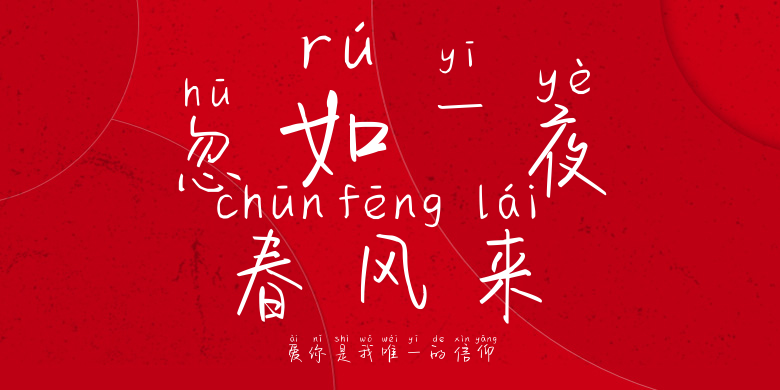
爱你是我唯一的信仰
爱你是我唯一的信仰,这款字体结构工整、笔画清晰,兼顾美观与易读性,适用于标题、正文、海报、包装、LOGO 等多种场景。字形优雅稳定,风格百搭耐看,适配日常排版与创意设计,让文字呈现更舒适、更具质感。爱你是我唯一的信仰一笔一画,皆是细节,以均衡的比例、流畅的线条打造舒适视觉体验,字形端正大气,风格简约现代。无论是商业设计、品牌宣传还是日常排版,都能轻松驾驭,让文字更有格调与力量。爱你是我唯一的信仰字体下载。